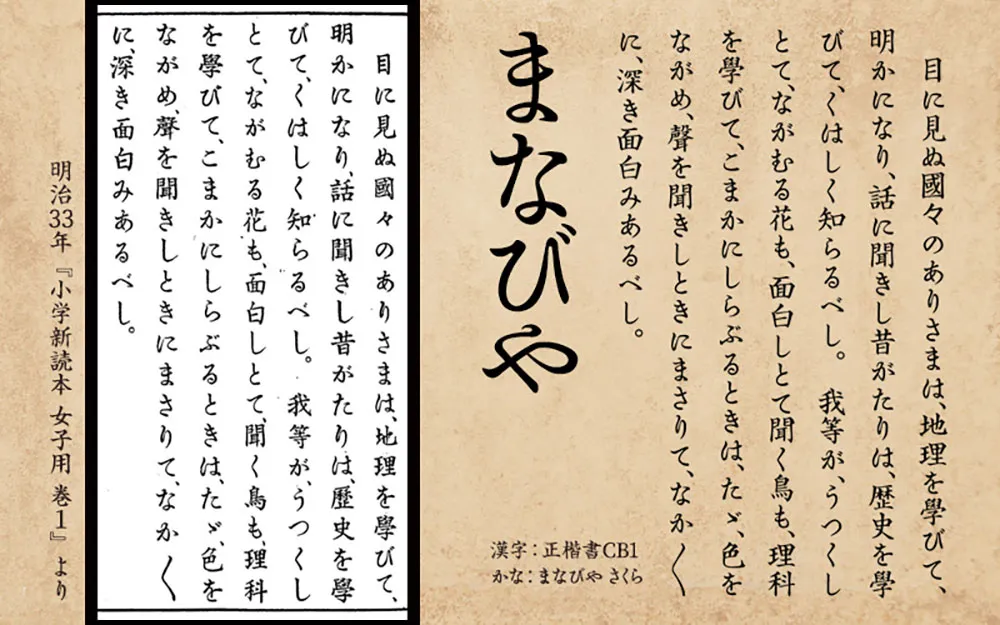
まなびや(Manabiya)這是根據明治時代的教科書創建的平假名字體。
*出處:國立國會圖書館數字館藏
文學社編輯部編《新小學讀物:女生專用第1卷》文學社(明治33年)
我創造了一些文本中沒有的人物來配合氣氛,或者用我自己獨特的解釋來創造它們。
這是僅適用於平假名和片假名的字體。
有兩種類型:ICHO與SAKURA
明治時代の教科書を元に作成したひらがなフォントです。
※資料:國立國會図書館デジタルコレクション
文學社編輯所 編『小學新読本 : 女子用 巻1』文學社(明治33年)
文中になかったいくつかの文字は雰囲気を合わせて作ったり、かなり獨自の解釈で作成しています。
ひらがな・カタカナのみのフォントです。
ノーマルな『さくら』と、
古めかしい感じにガタガタしている『いちょう』の2種があります。
注:這款字體可以和源流明體、源雲明體、英椎楷書搭配使用效果更佳